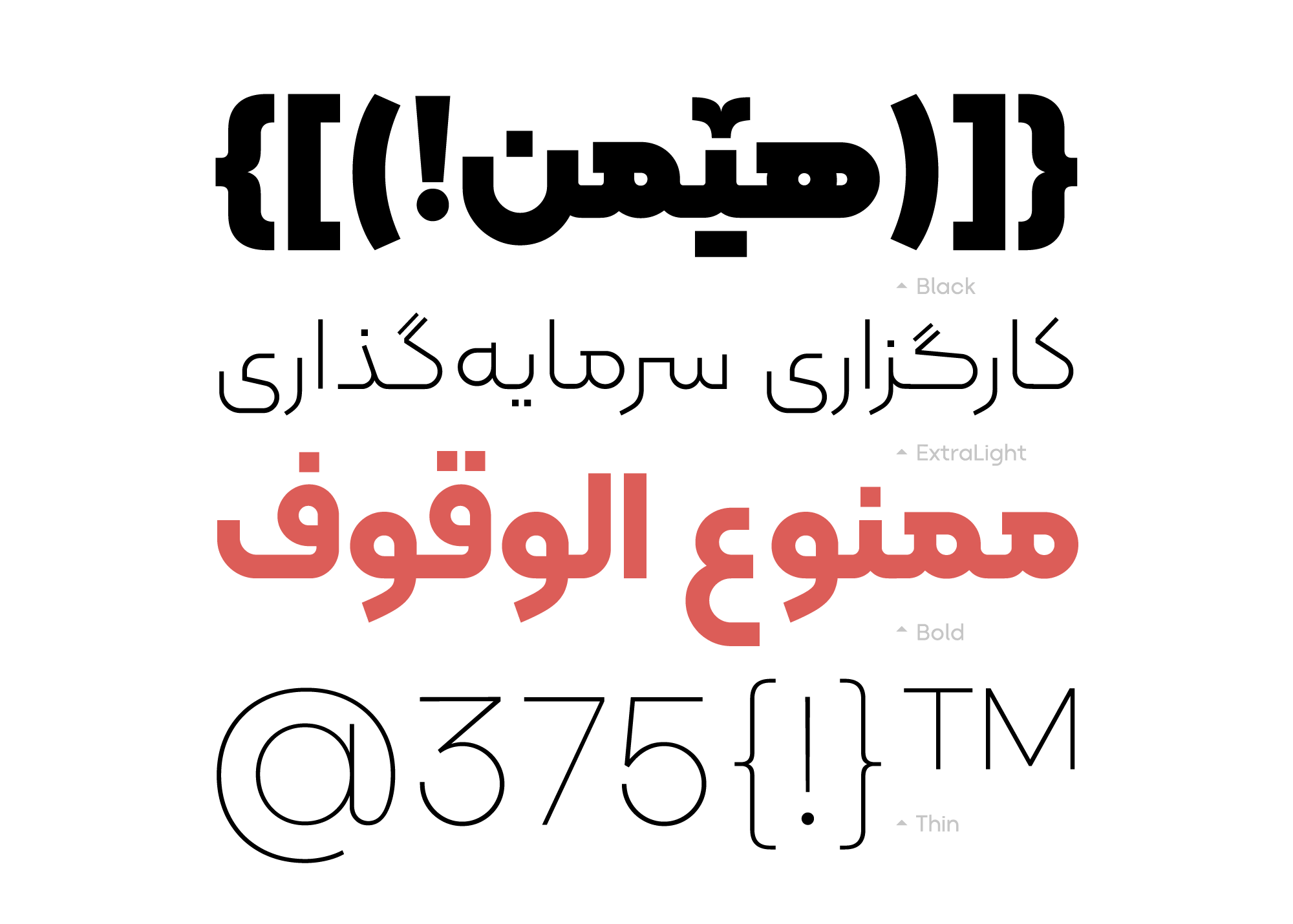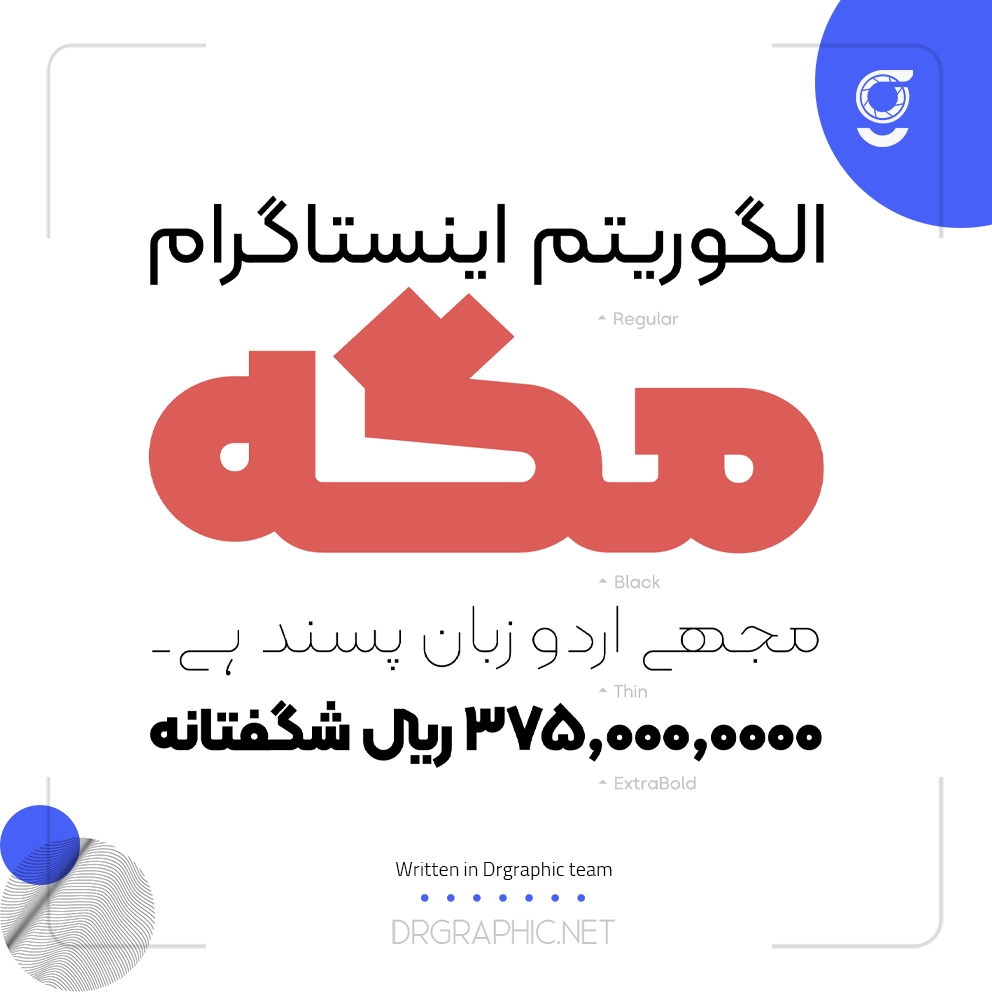
فونت کلمه، ساختاری هندسی و منظم دارد. استخوانبندیِ اندامِ این قلم به شما فضایی شسته و رفته ارائه میدهد. با دکترگرافیک همراه باشید.
پویایی و انرژیِ فونت کلمه ، برای استفاده در اکثر آثار تبلیغاتی بهویژه برای استارتاپها و کسبوکارهای خلاق و نوین بسیار مناسب است.
فونت کلمه، قدرتمند و خودنماست؛ در متنهایی که تلاش دارند ویژگیها و تواناییهای خاصی را برجسته کنند و نکاتِ طلاییِ موضوع را شاخص نمایند، “کلمه” این قدرت را به آنها میدهد.
تایپفیس کلمه برای زبان فارسی، عربی و انگلیسی طراحی شده است و از زبانهای اردو و کردی نیز پشتیبانی میکند.
نسخه چهارم خانواده فونت کلمه، با اصلاحاتی نسبت به نسخههای پیشین و اضافه کردن حالتهای جایگزین حروف و پشتیبانی از زبانهای جدید ارایه شده است.